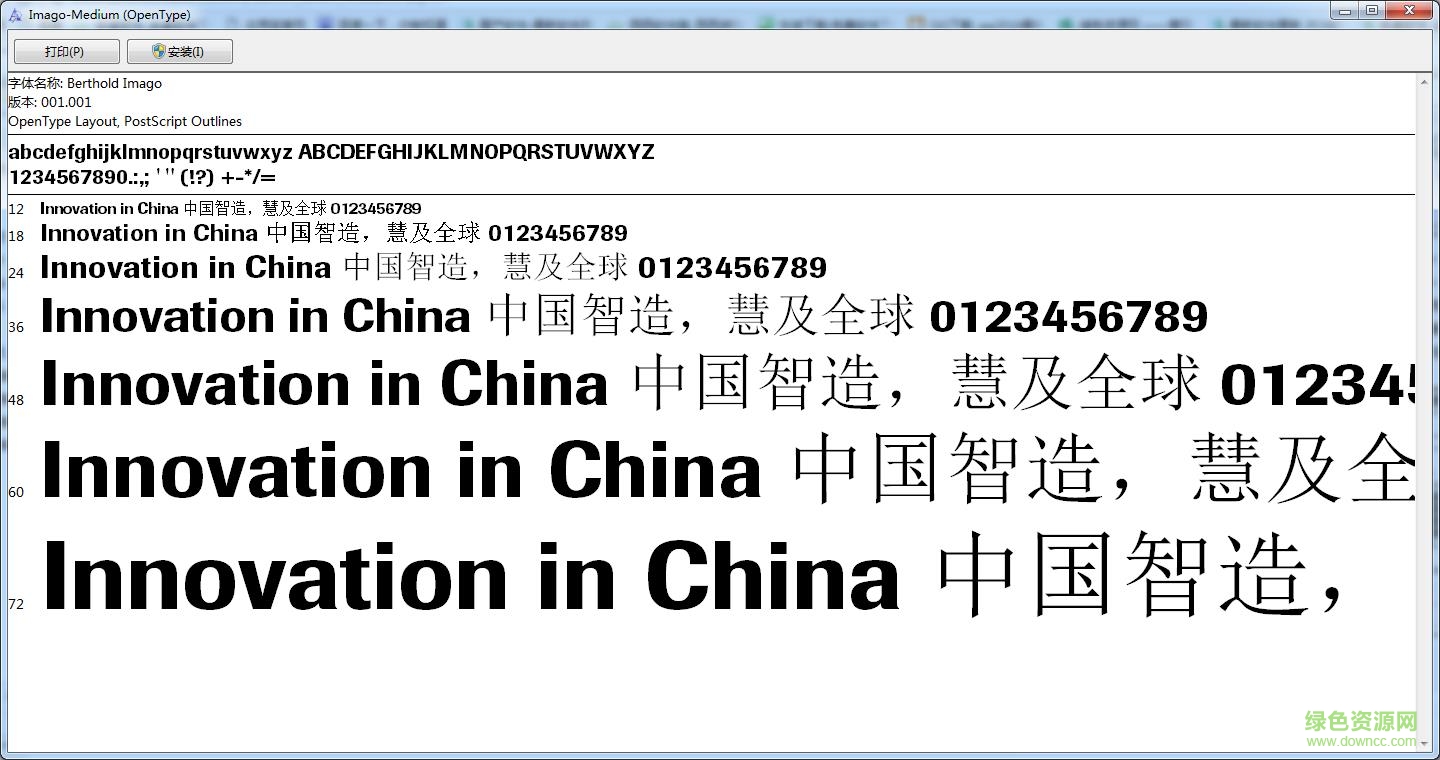
imago字體是一款能夠進(jìn)行影視制作,為用戶帶來不錯(cuò)視覺字體效果的特色字體樣式,其風(fēng)格十分端莊大氣,能夠運(yùn)用到各類行業(yè)當(dāng)中,不僅能夠進(jìn)行教學(xué)ppt制作,生活文檔制作更能夠在海報(bào)制作與藝術(shù)字設(shè)計(jì)當(dāng)中獨(dú)占鰲頭!
一款用于美工設(shè)計(jì)方面的英文字體,
該字體端莊雄秀、神韻超逸、圓融蒼潤,看上去十分美觀,整體效果非常統(tǒng)一,
且字庫完整,可以廣泛應(yīng)用于美術(shù)設(shè)計(jì)、廣告設(shè)計(jì)、宣傳海報(bào)、ppt、影視制作以及任何使用文字的領(lǐng)域!